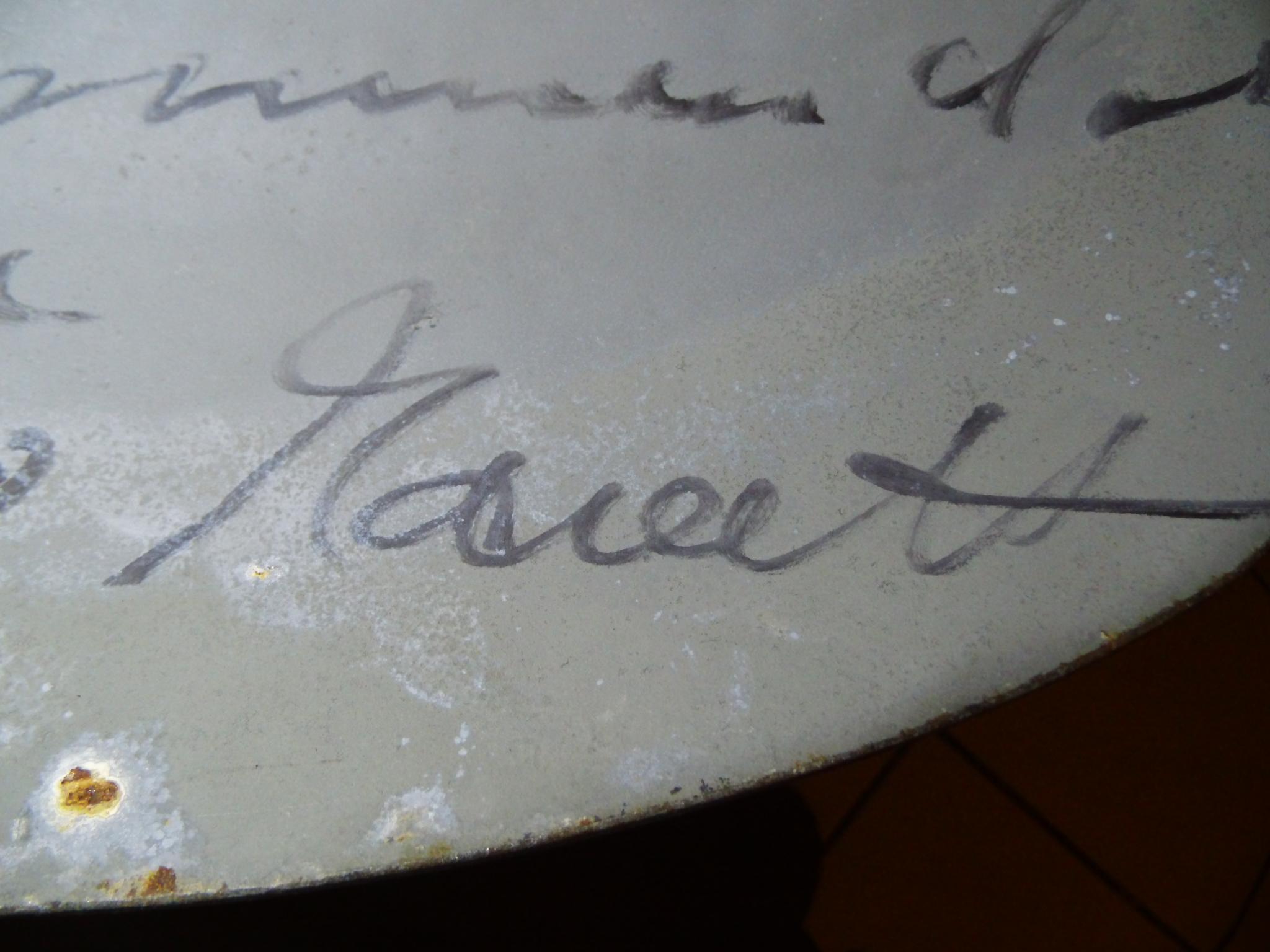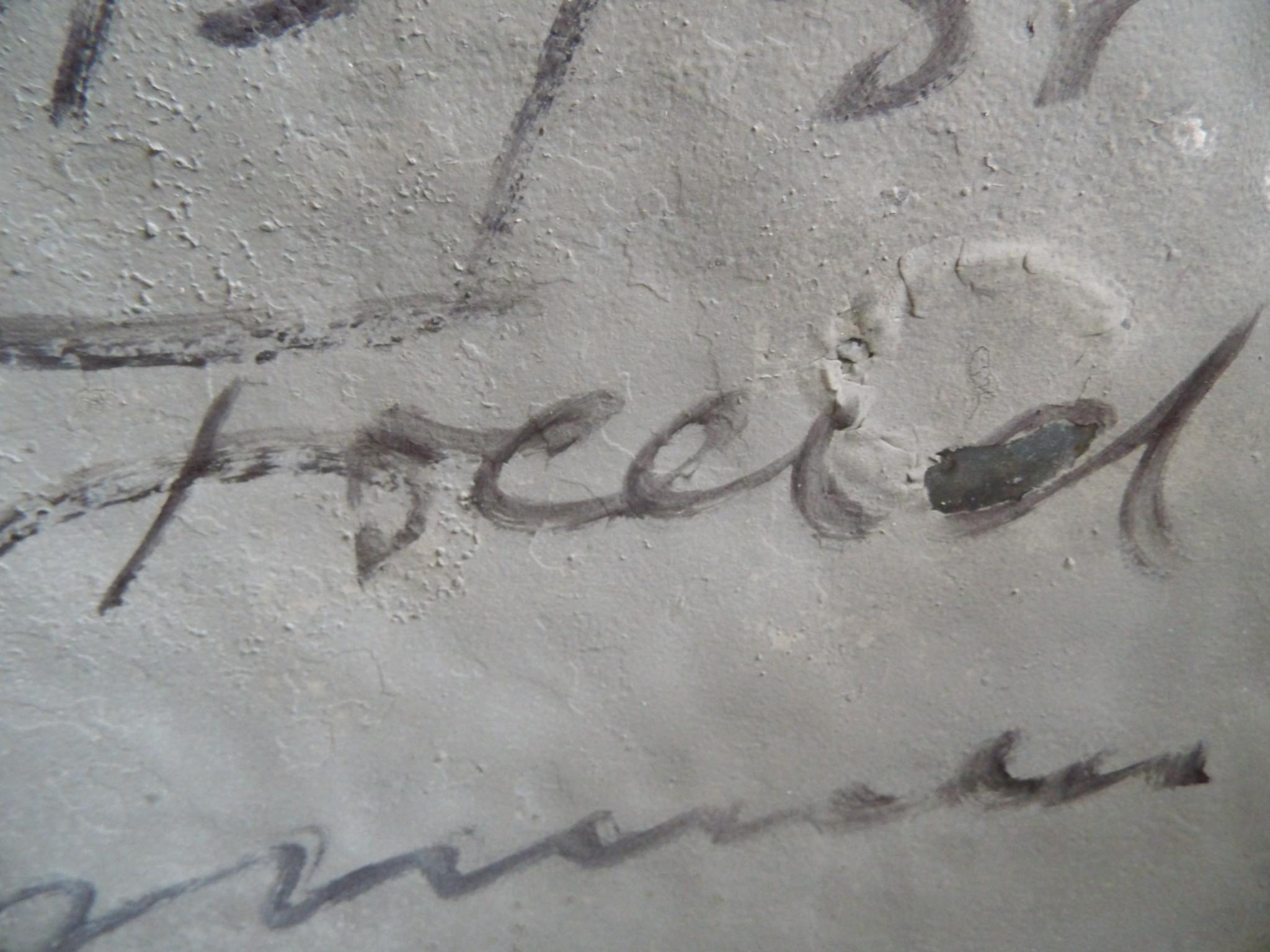
was ist das für eine Name ?
kann mir jemand sagen, was dort für ein Name geschrieben steht ?
Ich suche nur den unteren Namen auf den Fotos.
Mario ? Maria ??  und der Nachnahme.  Ist der erste Buchstabe ein M oder N ??
Ich lese dort "Marett". Der Kontext würde vielleicht weiterhelfen – in welcher Sprache befinden wir uns?
da der Vorname Maria oder Mario ist ??, vermute ich ursprünglich einen ausländischen Namen.  Restliche Schrift ist in deutsch geschrieben.   Ist es eine Maria ?.
Bist due Dir mit dem Nachnahmen sicher ???
Es könnte ein Künstlername sein. Wichtig ist auch ob es Maria oder Mario ist
Außerdem wäre es für die Entzifferung der Schrift außerordentlich hilfreich, weitere Schriftmuster zu sehen. Es hilft bei der Interpretation eines Zeichens, wenn man dieses mit weiteren Schriftproben vergleichen kann (Gerade auch für die Frage, ob es Maria oder Mario heißt!). Magst Du uns weitere Textstellen zeigen?
Durch den Doppelpost ist die Maria in der Drucktechnik gelandet. Ich finde das »a« bei Maria weicht sehr vom vermuteten »a« im Nachnamen ab.
mh....und was nun. Ich blicke da nicht mehr durch, was es genau heißen könnte.
Beim Nachnamen könnte hinten auch ein s sein – wegen des zurückschwingenden Bogens ...
Und wenn ich mir den Freund angucke, könnte das ganze auch ›Manuts‹ o. ä. heißen :-?
Bitte um Verständnis.  Es ist etwas persönliches
Im Prinzip gern. Nur wenn du nicht einmal den Namen des Schreibers kennst, wird das Geschriebene auch kaum an dich gerichtet gewesen sein. Warum hast du dann, gerade wenn der Text in irgendeiner Weise sensibel oder pritvat sein mag, ein Recht, ihn zu entziffern, das Anderen nicht zusteht? Das kann alles legitim sein, keine Frage. Aber leider treiben sich im Netz eben auch jede Menge Schufte herum, die die Hilfsbereitschaft Anderer für allerlei Bosheiten ausnutzen. Vielleicht kannst du ja ganz allgemein erklären, worum es geht. (Und das könnte dann auch bei der Entzifferung helfen, wenn wir mehr über Epoche, Medium und andere Umstände wissen.)
oh je....nein nein.  Keine komische Absicht.  Der Name steht im Bezug zu einem Künstler auf einem Objekt.  Diese Maria oder Mario suche ich nur vom namen her.  Da dieser der schenkende an den Künstler war.  Bitte nicht so kompliziert machen.  Es muß aber auch keiner mehr überlegen. Ich möchte keinen verunsichern.  Ich werde mich an einen Gutachter wenden, den ich bereits gefunden habe.  Sorry für die unannehmlichkeiten.